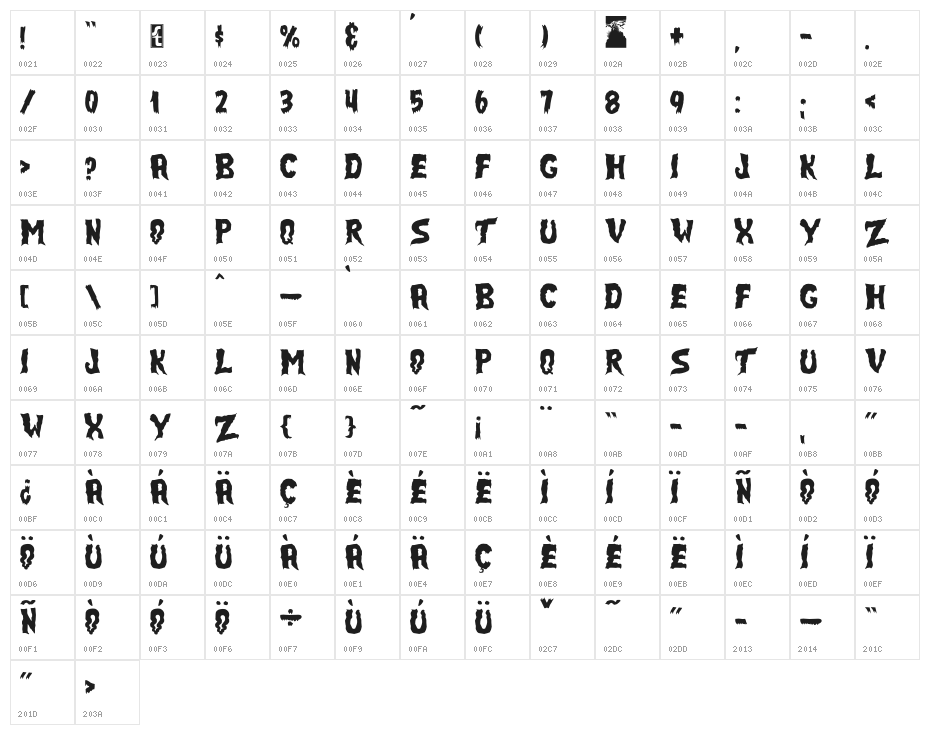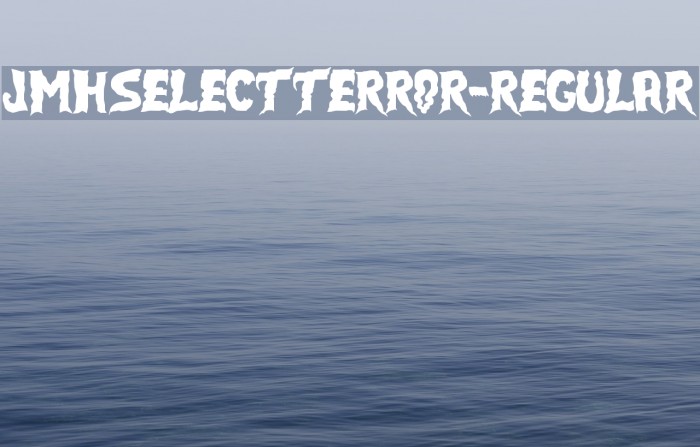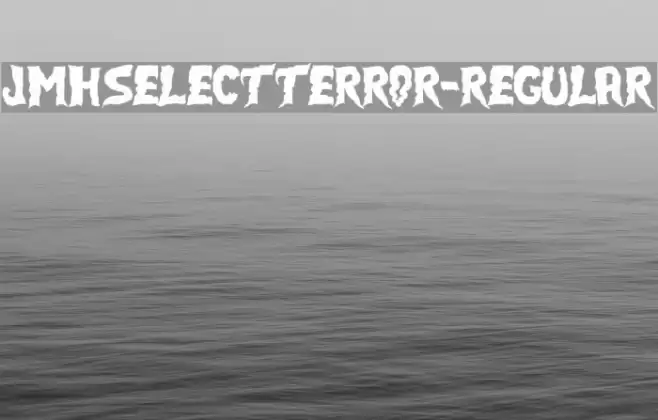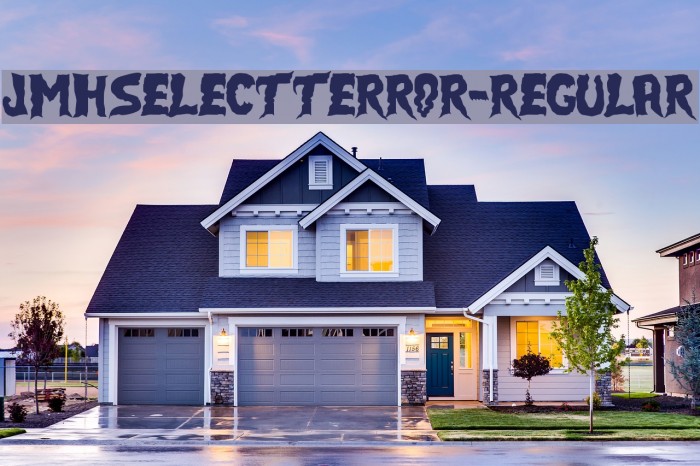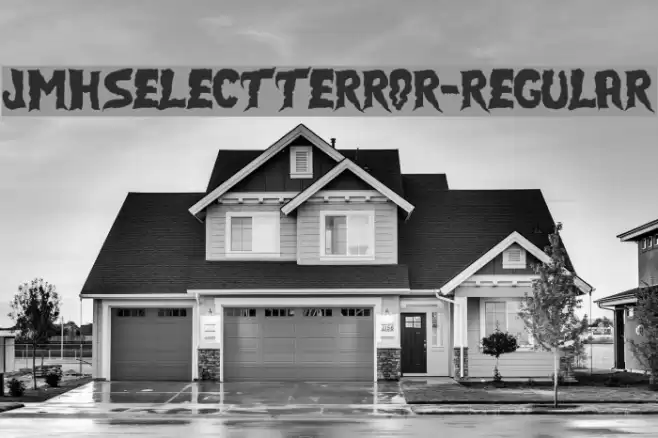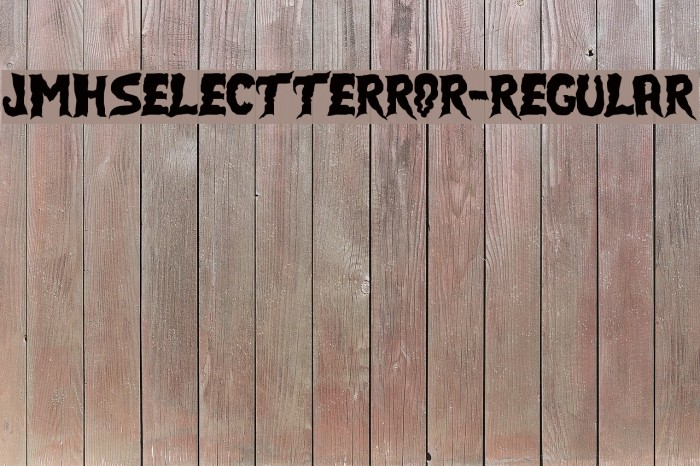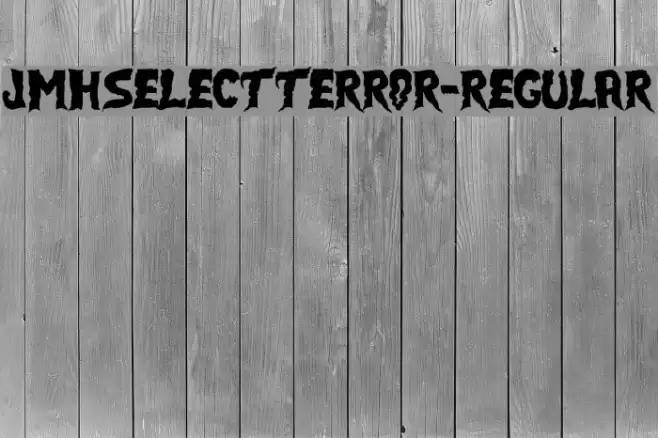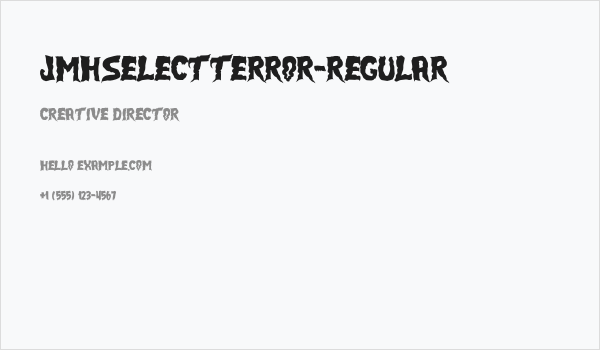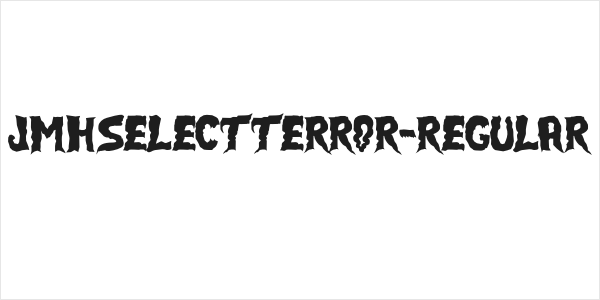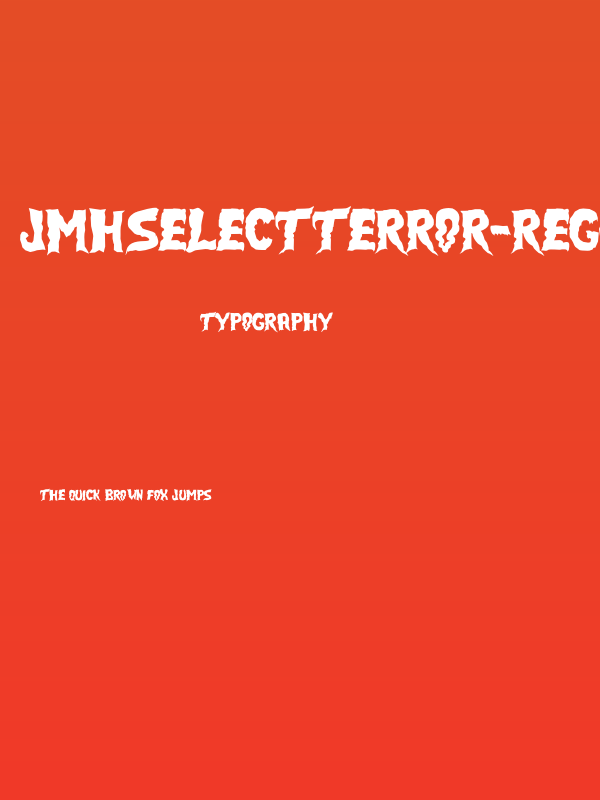
JMHSELECTTERROR-Regular Font
| Projets proposés | Ideal for Halloween posters, horror movie titles, spooky event invitations, and themed merchandise. |